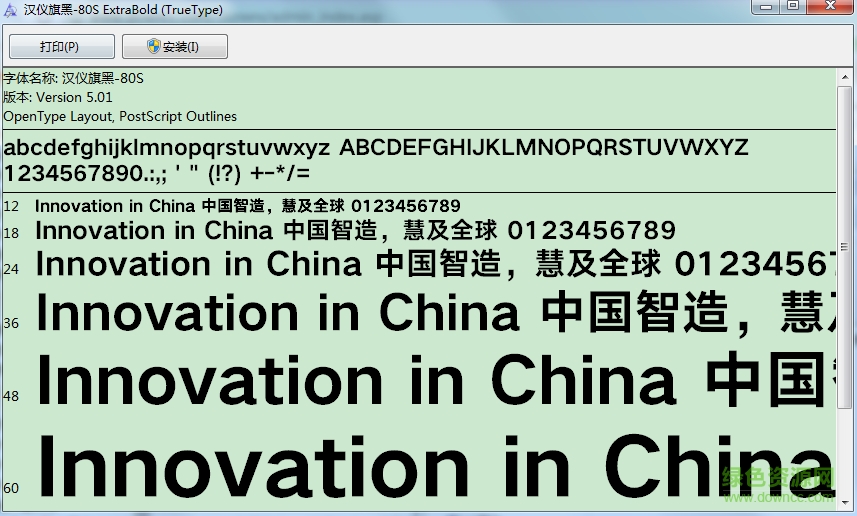
hyqihei hzs字體也就是漢儀旗黑-80S字體,這款字體是漢儀字庫里面的一款常用字體,這款字體筆畫粗細均勻,結(jié)體嚴(yán)整茂密,清晰易讀,非常好用!喜歡的朋友可以來綠色資源網(wǎng)免費下載使用喲!
漢儀旗黑是由三個系列字體(長、方、扁)組成的一個龐大而完整的家族字體,從最細的25到最粗的105,共計15個字重,是迄今為止國內(nèi)最大、最豐富的字重的家族字體,可以滿足企業(yè)多渠道,全方位的內(nèi)容設(shè)計以及定制化需求,實現(xiàn)企業(yè)品牌形象在各渠道的統(tǒng)一呈現(xiàn)